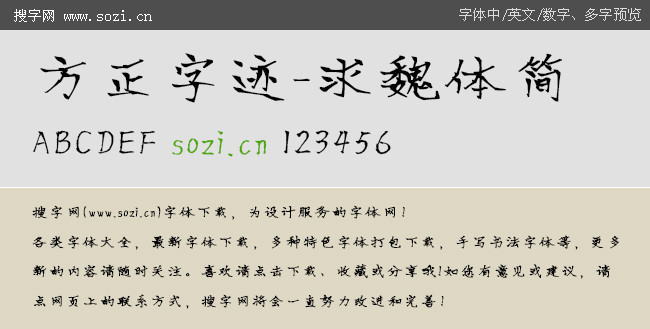
方正字跡-求魏體簡
搜字網(wǎng)提供一款方正字跡-求魏體簡中文字體下載,這是一款通過方正“寫字先生”APP,用手指在手機(jī)屏幕上逐字寫成的字庫。屏寫或許將成為未來書寫的新方向。作者結(jié)合魏碑風(fēng)格和個人成熟的書寫技能,巧用系統(tǒng)預(yù)置的筆觸效果,探索性地創(chuàng)出了一款體勢穩(wěn)健,精神勃發(fā),別開生面的屏寫字體。適合一些需要個性化表達(dá)的用途。